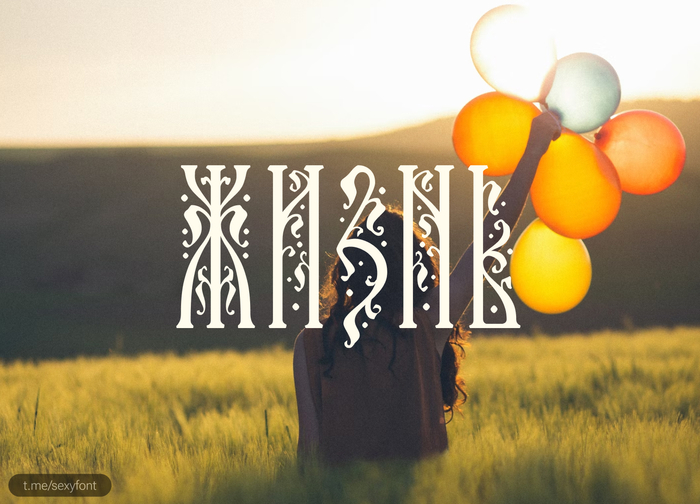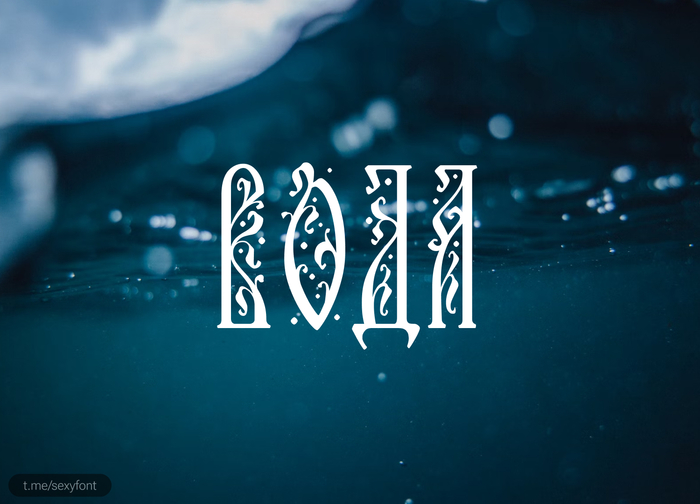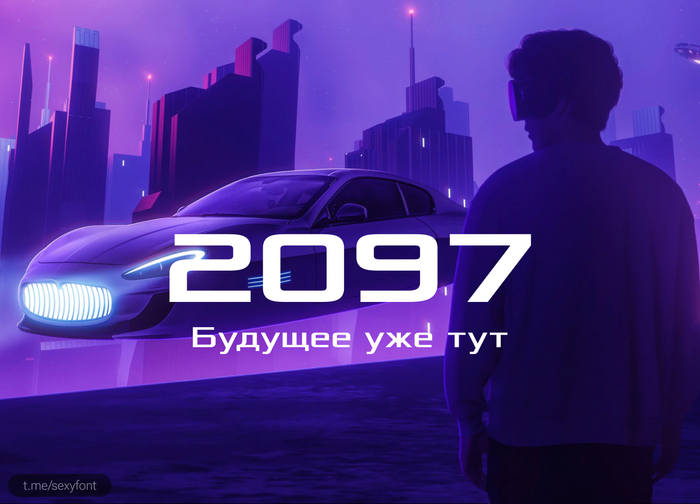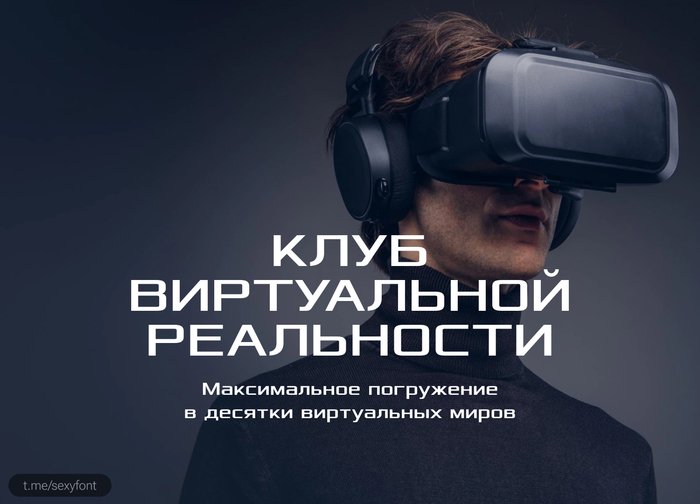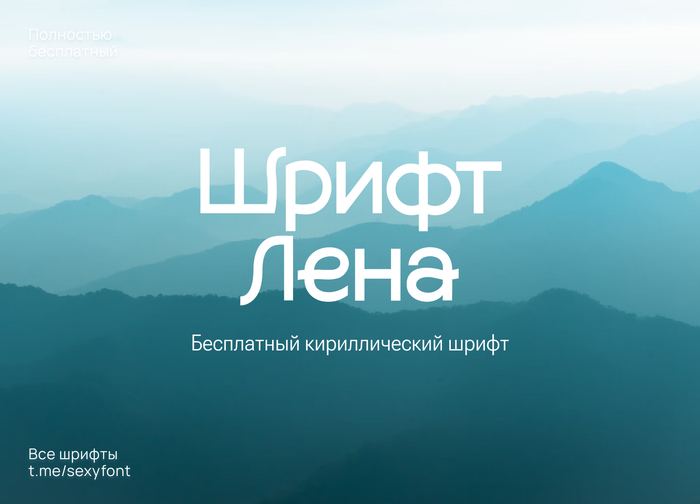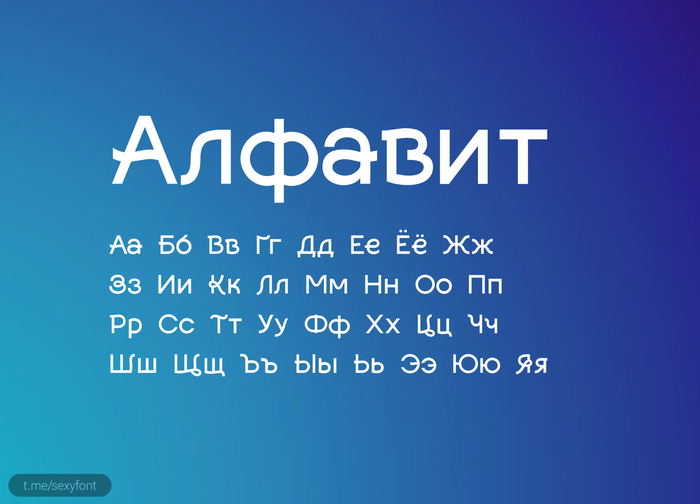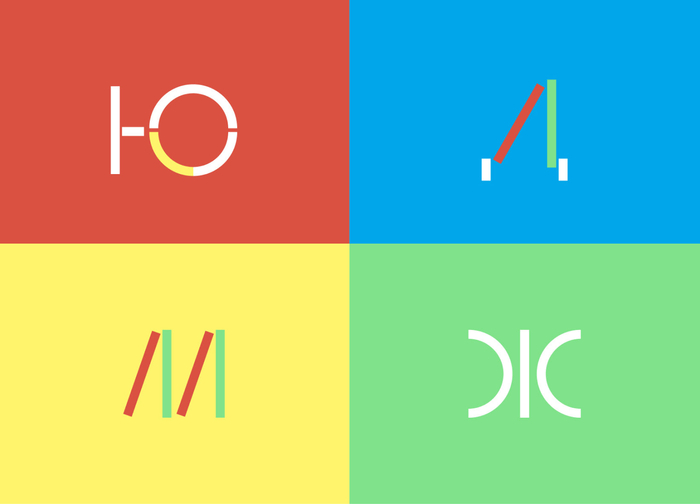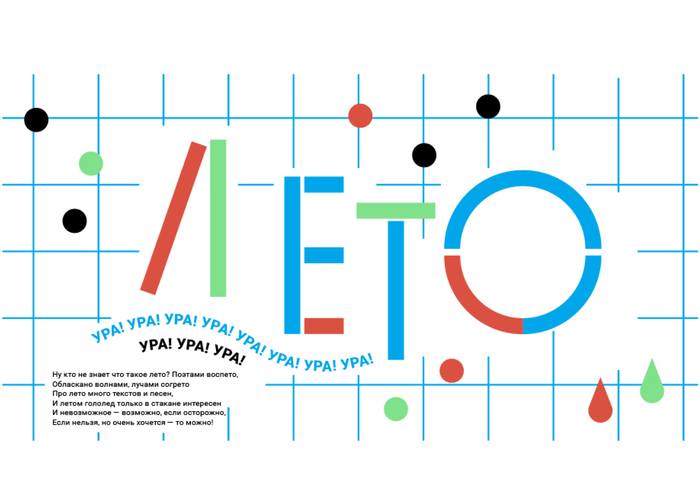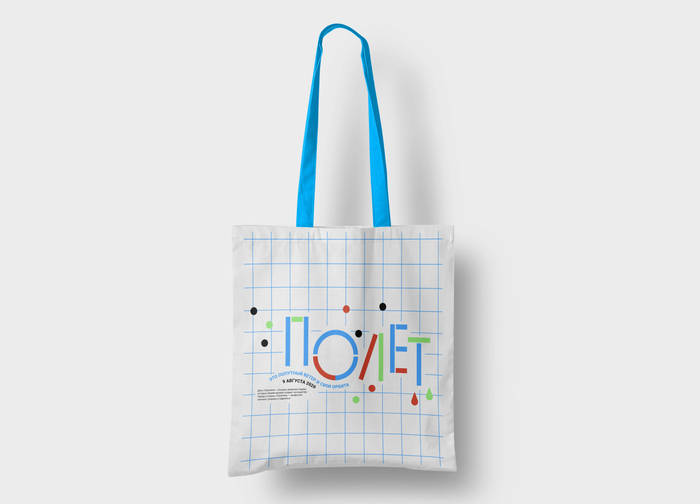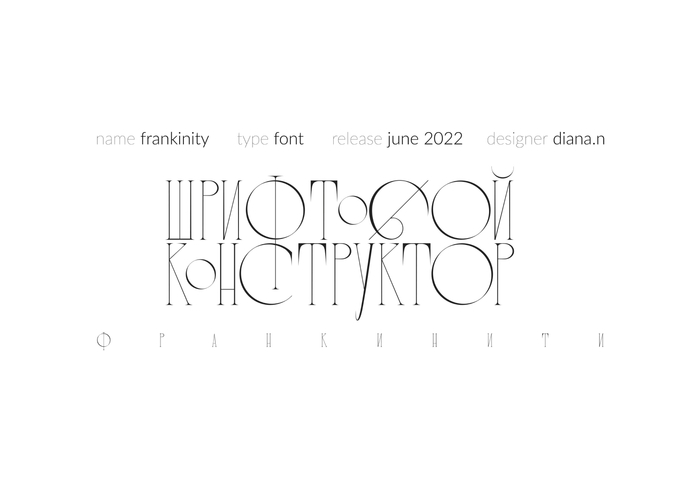
Шрифт Елена
Еще один шрифт, именуемый Еленычым.
Совсем в другом стиле. Сказочный прям. Ни*рена не читаемый, но красивый) В данном случае текст лучше использовать, как форму декорации, а не повествования. Не знаю как тебе. А мне нраица)
Автор: Дмитрий Тектов
Шрифт Xolonium
Футуристичный шрифт Xolonium. Главное, что он хорошо читается, как в крупных заголовках, так и в обычных абзацах. Бесплатный для личного и коммерческого использования. Автор: Severin Meyer
Шрифт Лена
Бесплатный, кириллический. Я написал автору и уточнил. Красивые волнистые буквы идеально подойдут под многие темы. Пользуйся. Автор шрифта: Vsevolod Abramov
Бесплатный шрифт "палочки" sticks
Вот и слово готово. Дизайнер этого шрифта любил в детстве составлять слова из ручек и карандашей. Теперь разработал это творение и поделился с миром. Автор: Alena Madyanova
Шрифт FRANKINITY. Бесплатный
Откровенность. Так переводится название этого изящного шрифта. Читаемостью он похвастаться не может. Но зато как красиво соединяются в нем буквы. Лигатура нравится. В каком-нибудь постере я бы точно использовал. К тому же автор расщедрился. Шрифт бесплатен для коммерческого использования) Автор: Diana N
Шрифт RIVERHACK. (кириллица)
Клевый рукописный шрифт RIVERHACK. Автор оригинала: Gabriela Goodwin Автора кириллизации к сожалению не нашел) Источники ведут на группу, к которой закрыт доступ.
Кириллица в восточном стиле. Бесплатная
Яххо друзья! Сангха. Еще один кириллический шрифт в восточном стиле. Вполне читаемый в коротких заголовках. Автор: Anna Seslavinskaya Бесплатно для личных и коммерческих проектов.
Шрифт the Mosсow metro
Шрифт метро. Первый раз вижу шрифт, содержащий в себе цветные буквы) Правда в фигме не сработало, а в фотошоп все гуд. Бесплатный для использования в любых целях. Автор: Nadira Filatova